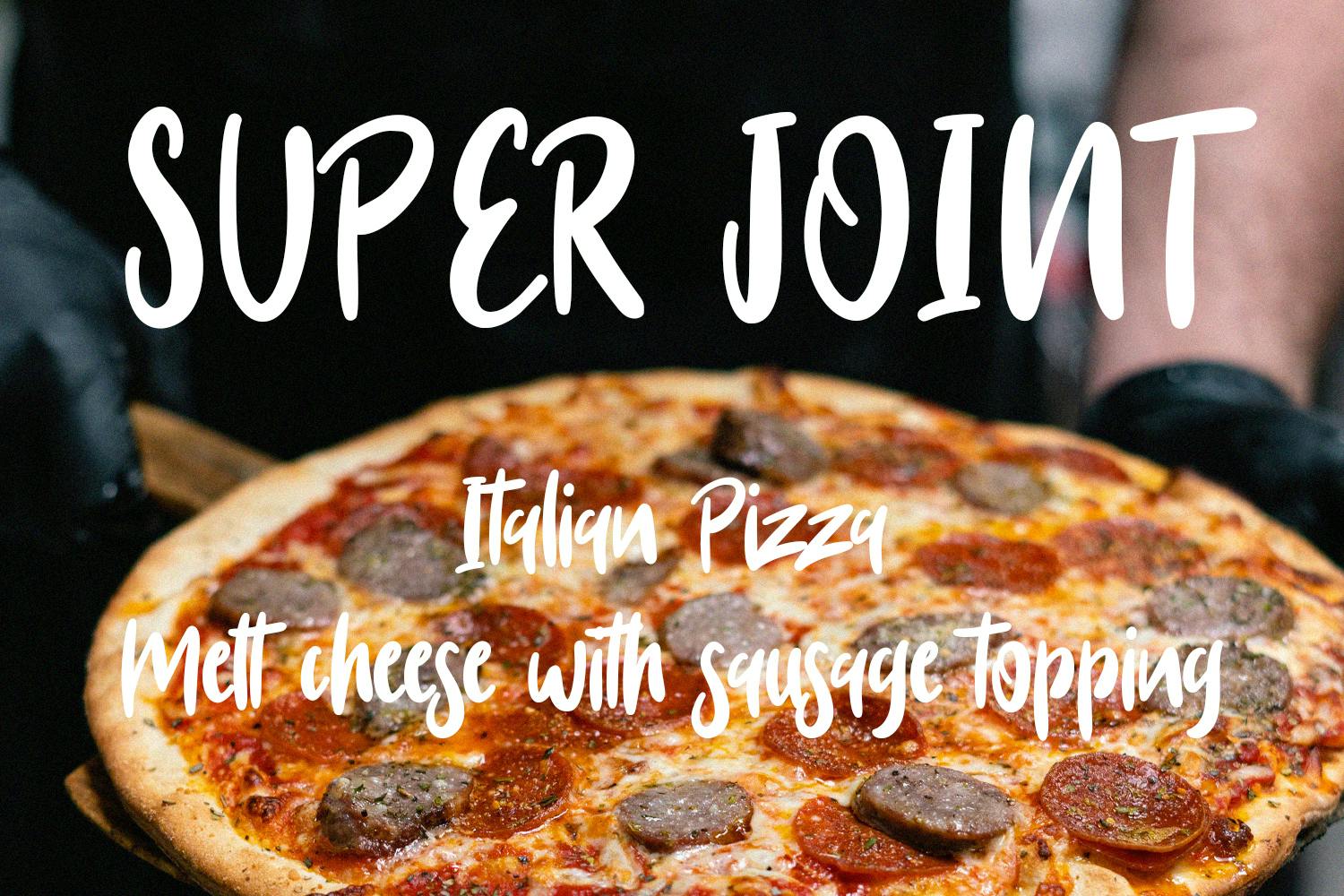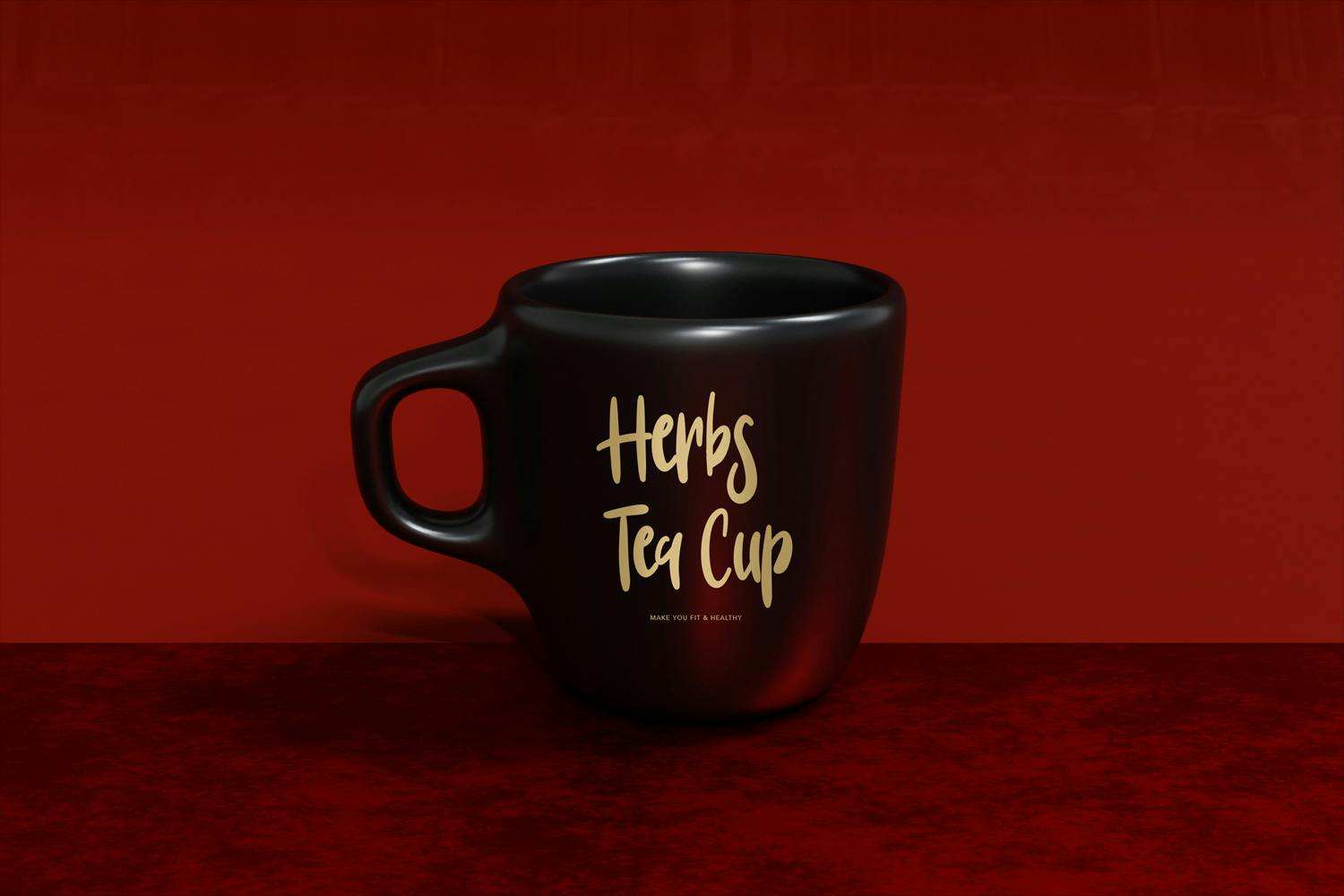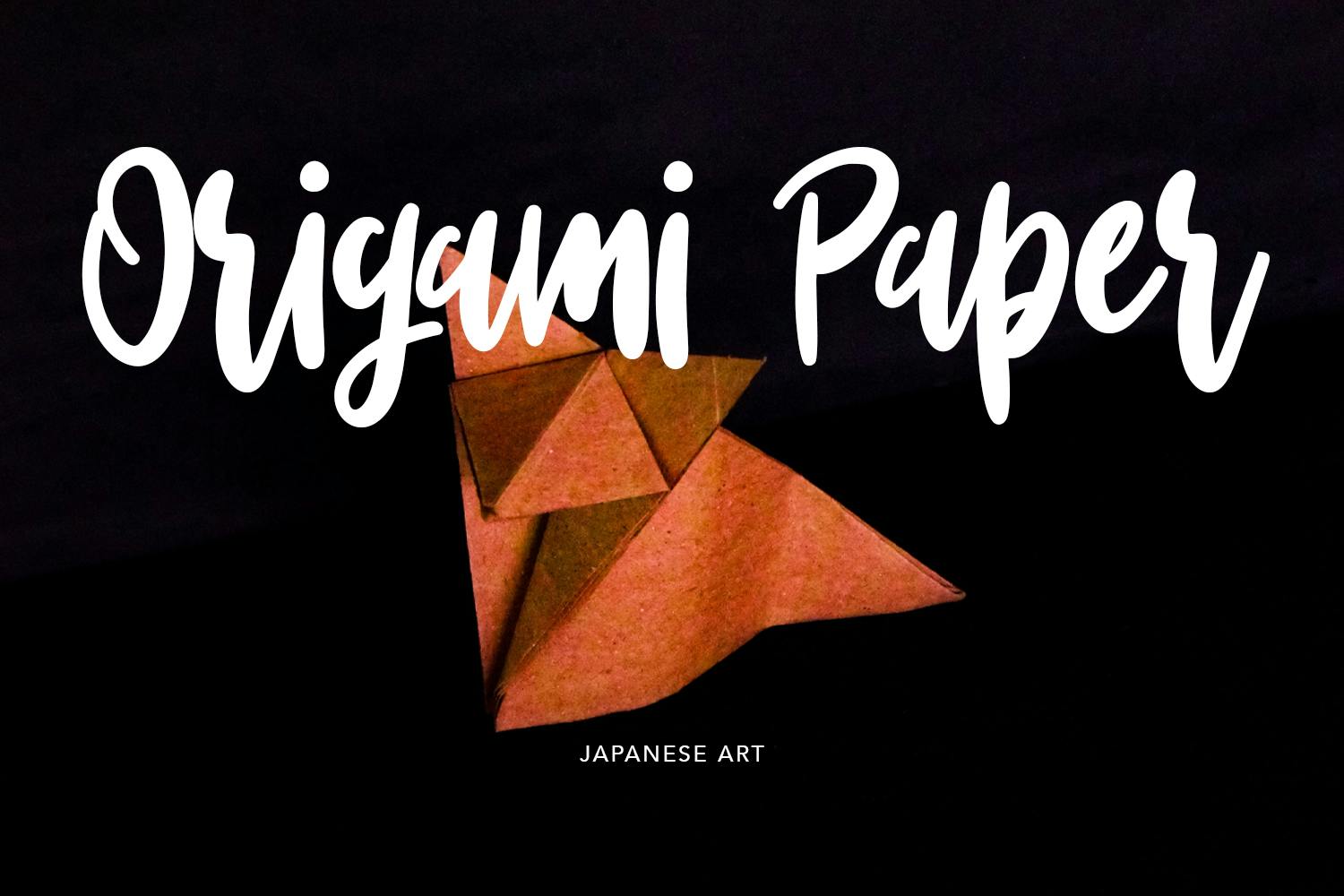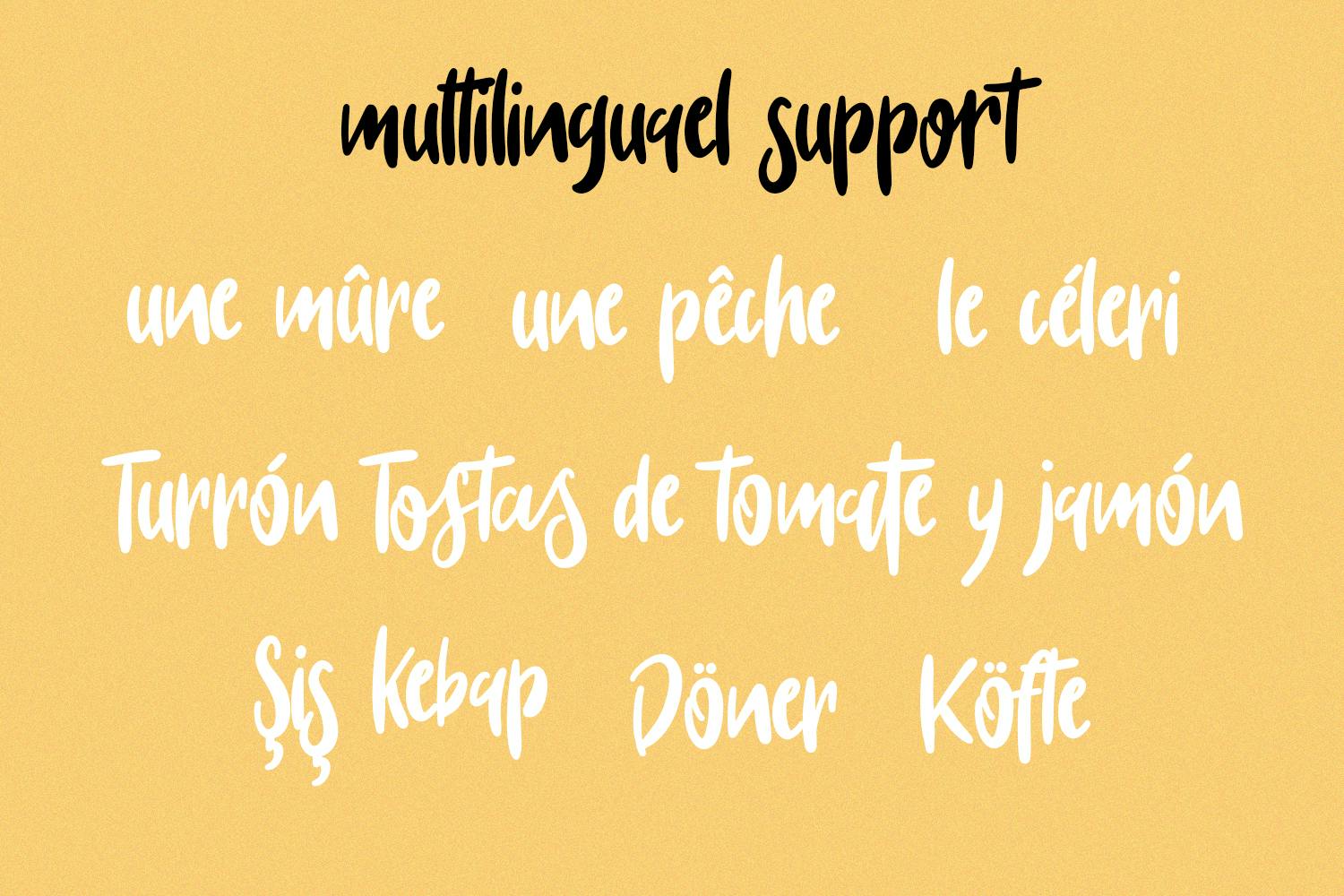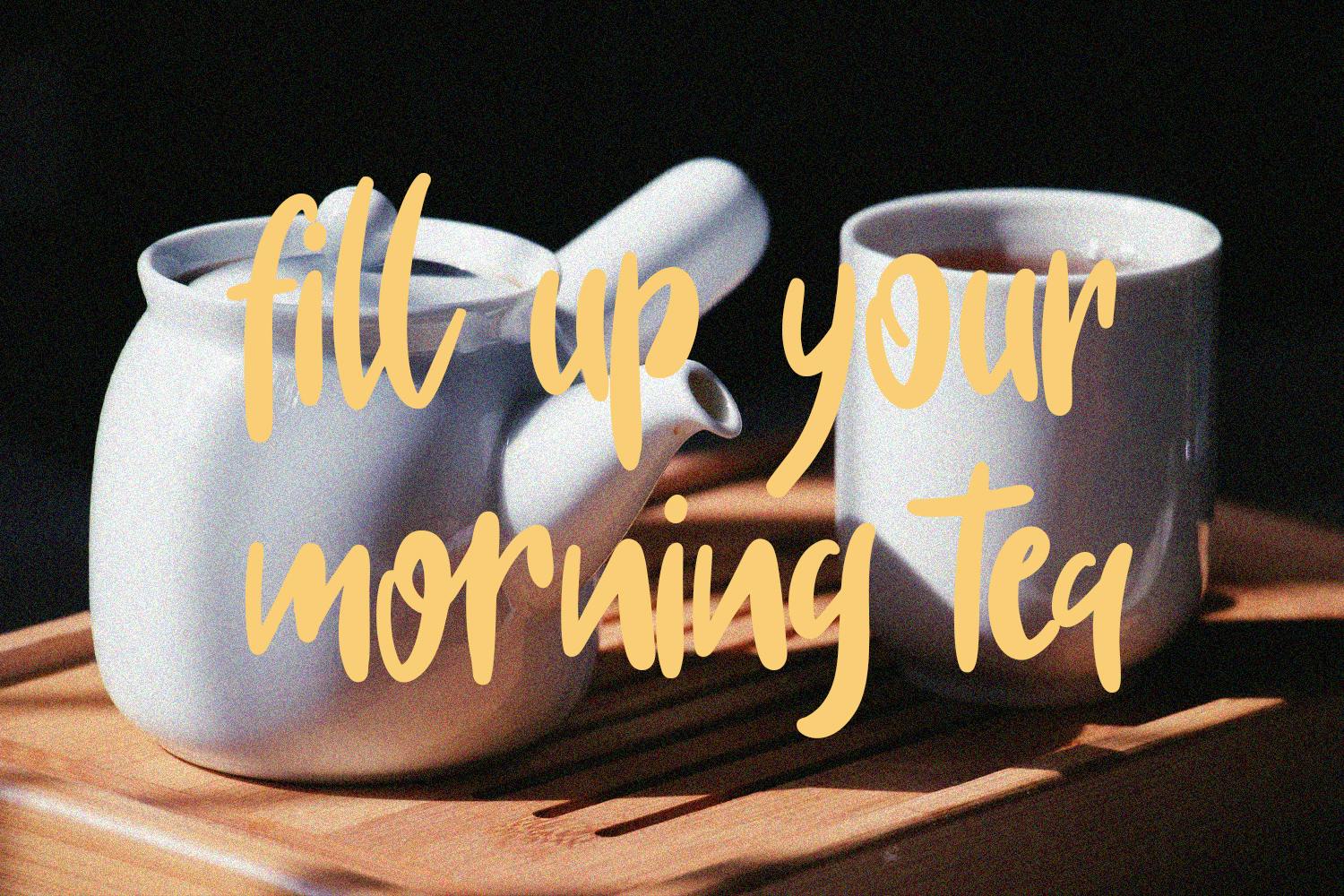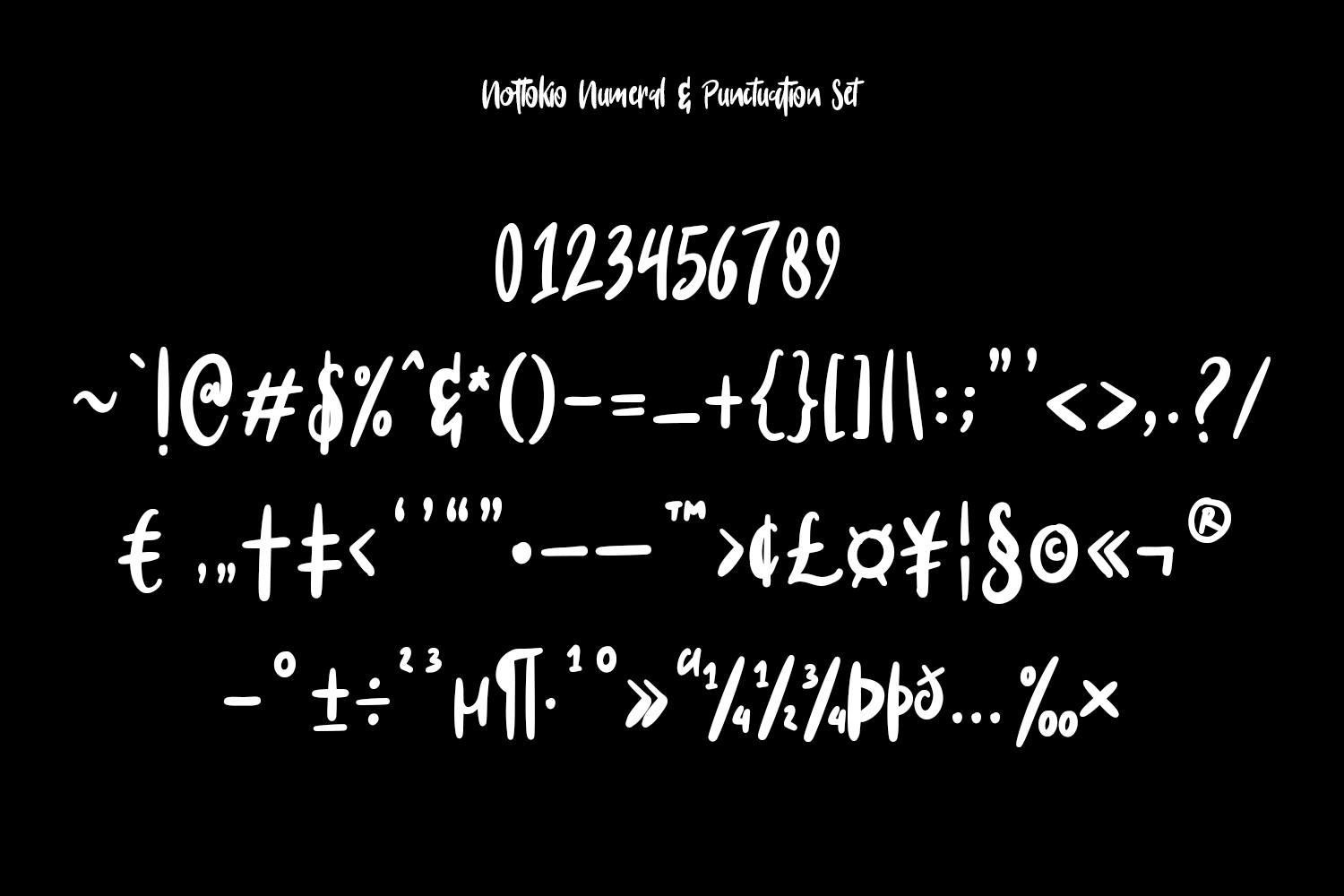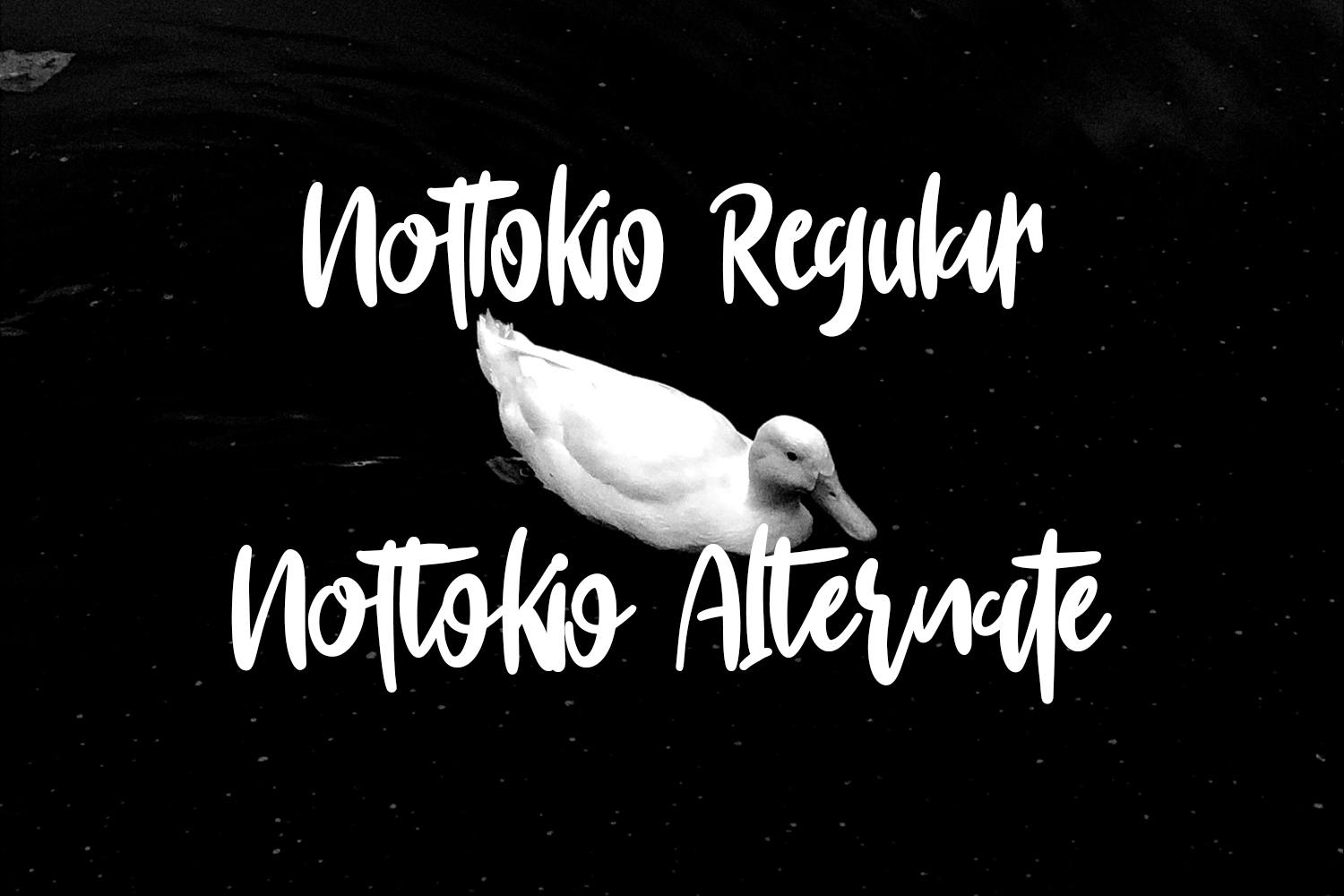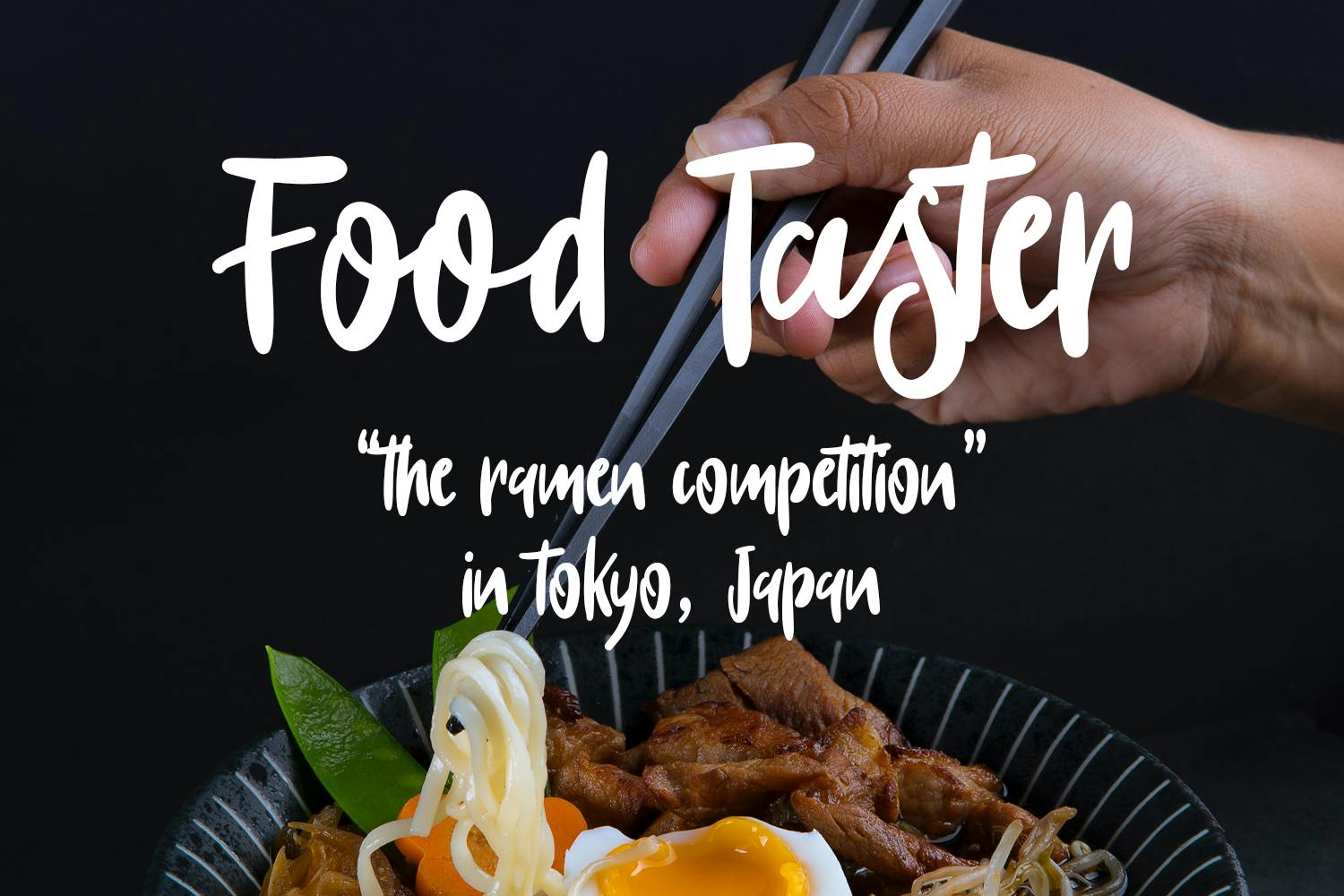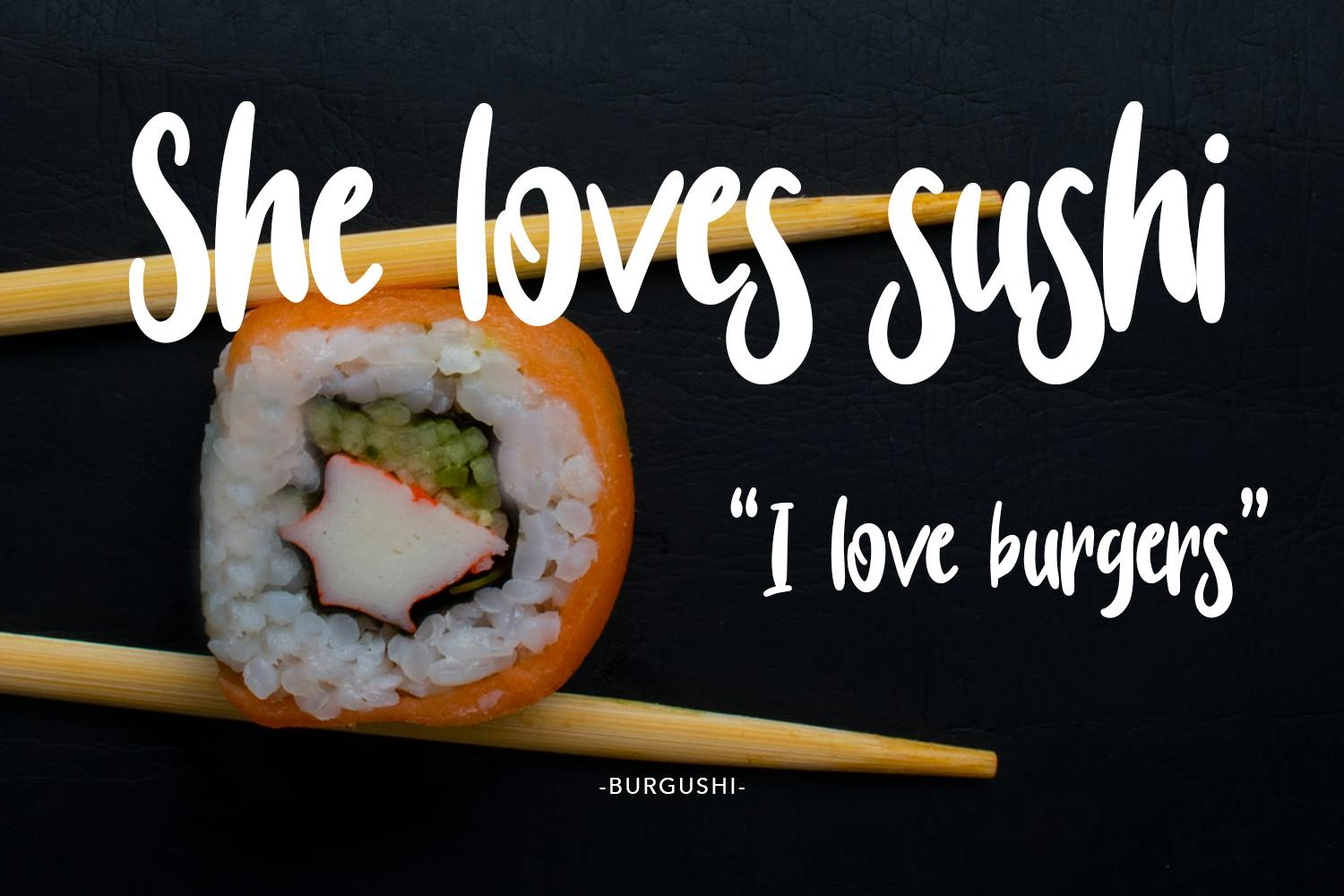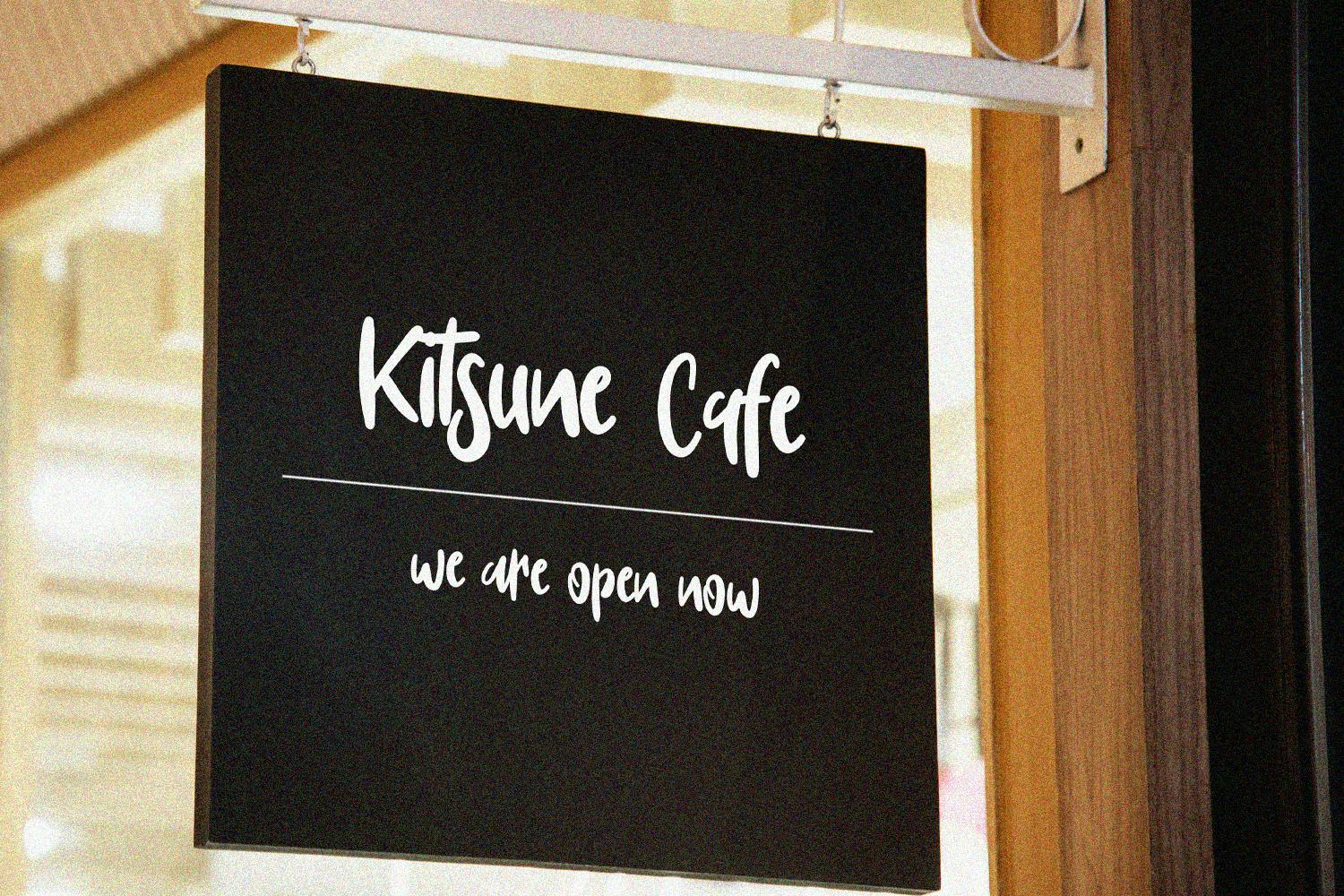
به طراحیهای خود حس دستساز و اصیل اضافه کنید. فونت "Nottokio Quoteable Logo Font" بهطور کامل برای طراحی امضا، لوازمالتحریر، لوگو، نقلقولهای تایپوگرافی، جلد مجله یا کتاب، هدر وبسایت، بروشور، پوشاک، برندینگ، طراحی بستهبندی و موارد دیگر مناسب است.